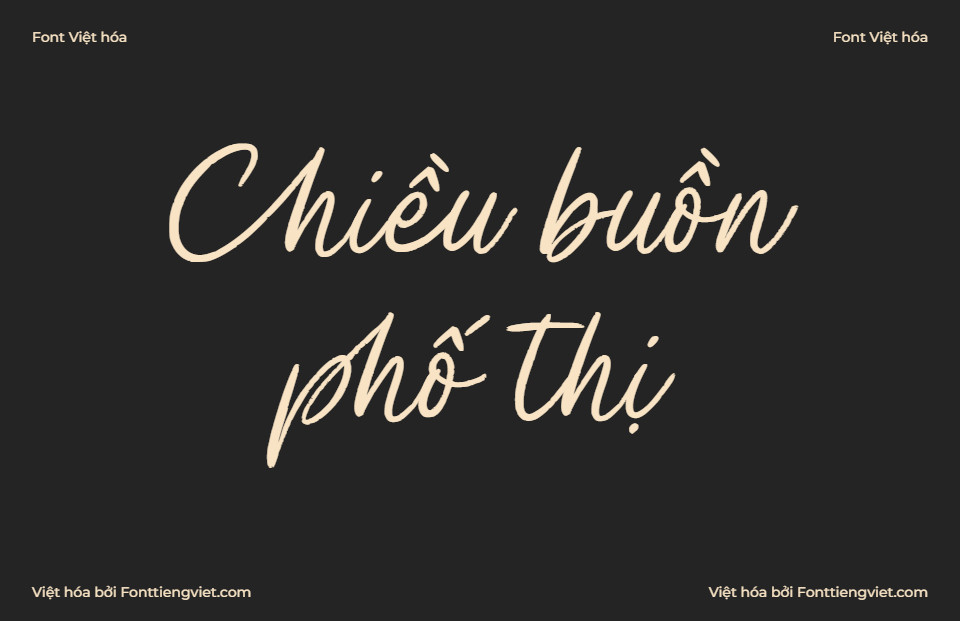
Font Việt hoá 1FTV VIP Billie James – Brush
Font Việt hoá 1FTV VIP Billie James – Phông chữ Brush nghệ thuật cực chất,Tải ngay Font Việt hoá 1FTV VIP Billie James phong cách brush độc đáo. Phông chữ thiết kế nghệ thuật, hỗ trợ gõ tiếng Việt chuẩn xác, hoàn hảo cho thiết kế logo, poster và banner.
Khám Phá Font Việt Hoá 1FTV VIP Billie James – Phong Cách Brush Đầy Nghệ Thuật
Bạn đang tìm kiếm một phông chữ phá cách, mang đậm dấu ấn thủ công để làm nổi bật dự án thiết kế của mình? Bài viết “Font Việt hoá 1FTV VIP Billie James – Brush” sẽ giới thiệu đến bạn một trong những siêu phẩm typography ấn tượng và độc đáo nhất dành cho designer.
1FTV VIP Billie James Là Gì?
1FTV VIP Billie James là một phông chữ thiết kế thuộc phong cách Brush (chữ cọ vẽ). Font chữ mang nét phóng khoáng, tự nhiên, bụi bặm nhưng không kém phần mạnh mẽ. Điểm giá trị nhất của phiên bản này là đã được đội ngũ 1FTV việt hoá hoàn chỉnh ở tiêu chuẩn VIP. Bạn có thể thoải mái gõ các ký tự tiếng Việt có dấu mà không lo tình trạng lỗi font hay xô lệch, giữ được trọn vẹn cái hồn của nét cọ gốc.
Đặc Điểm Nổi Bật Của Font Billie James Brush
• Đường nét chân thực: Từng nét phẩy, nét xước (dry brush) được tái hiện vô cùng sinh động, tạo cảm giác như được viết tay trực tiếp bằng mực nước lên giấy.
• Tối ưu dấu tiếng Việt: Các dấu câu được chăm chút tỉ mỉ, khoảng cách giữa các chữ (kerning) được tinh chỉnh chuẩn xác để tạo ra tổng thể hài hòa nhất.
• Tính ứng dụng đa dạng: Sự phá cách của font chữ này là lựa chọn hoàn hảo cho việc thiết kế logo thương hiệu, poster quảng cáo, typography áo thun, thiệp mời, hay các ấn phẩm truyền thông mang hơi hướng đường phố (street style) và vintage.